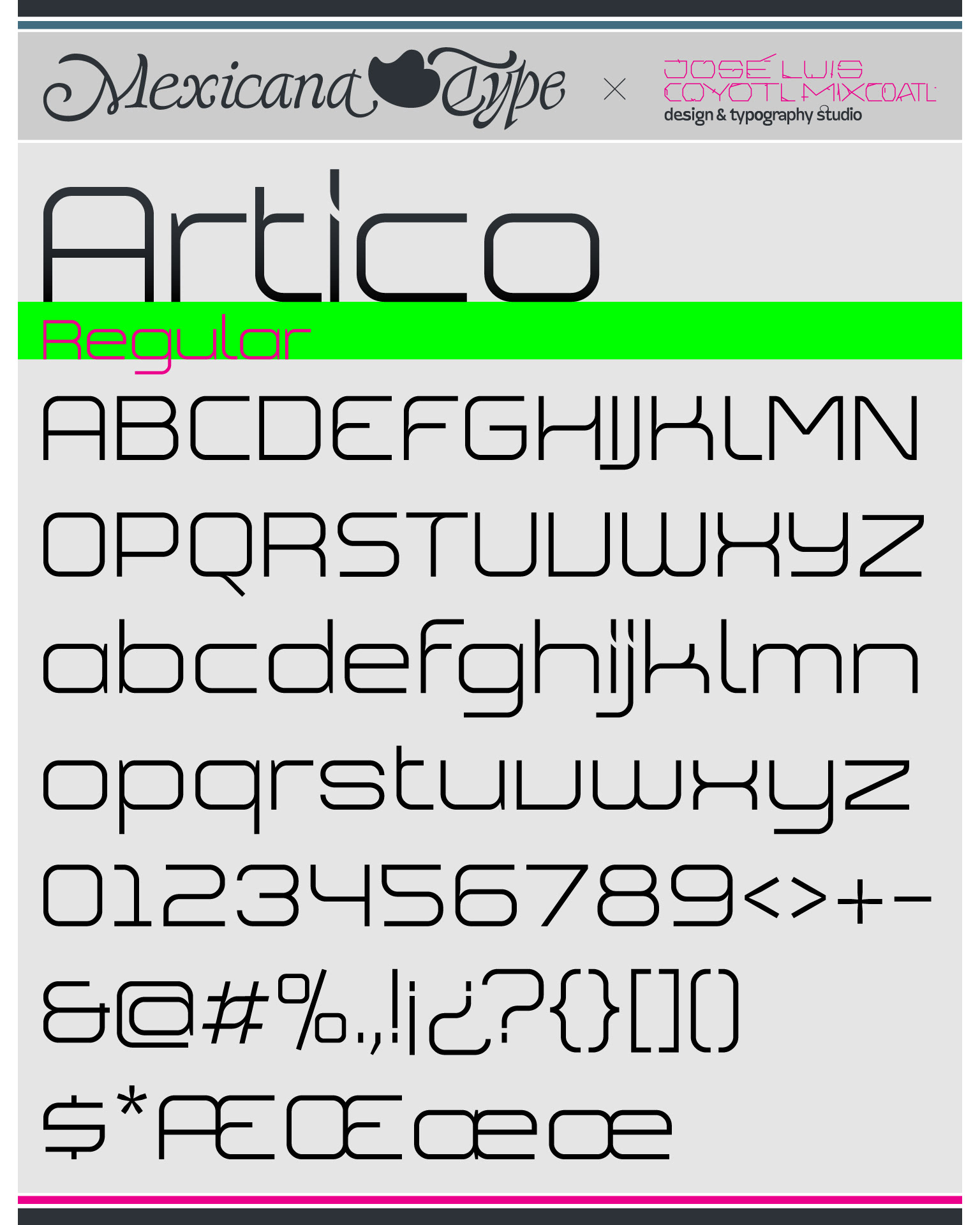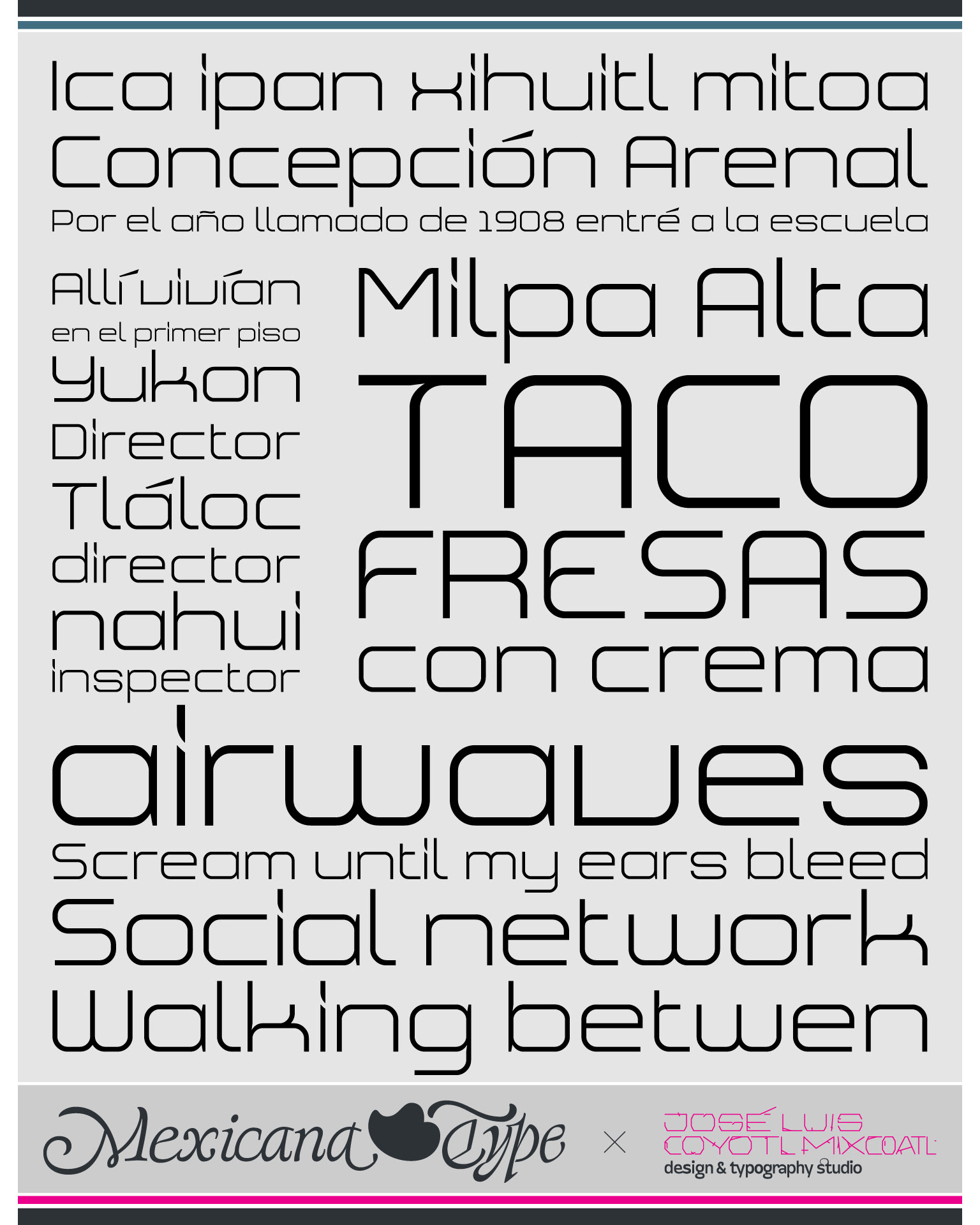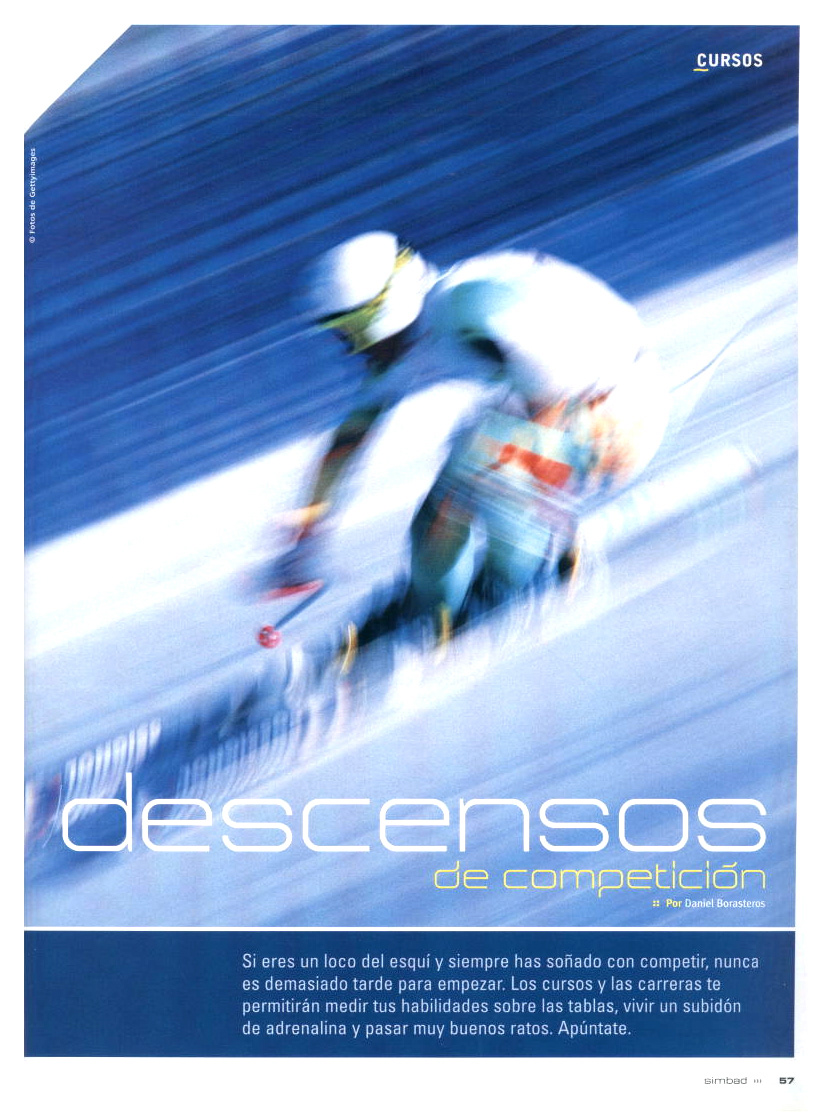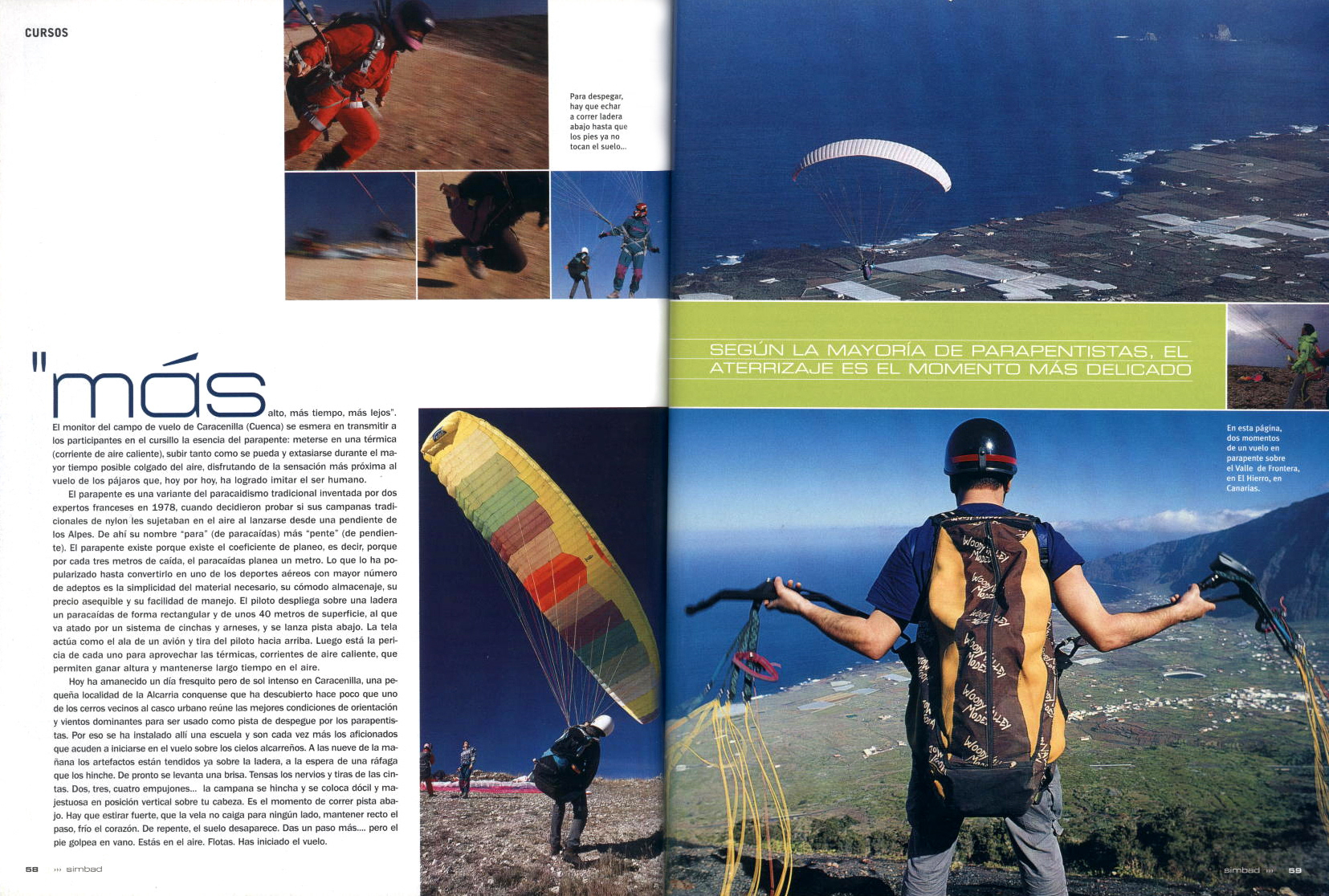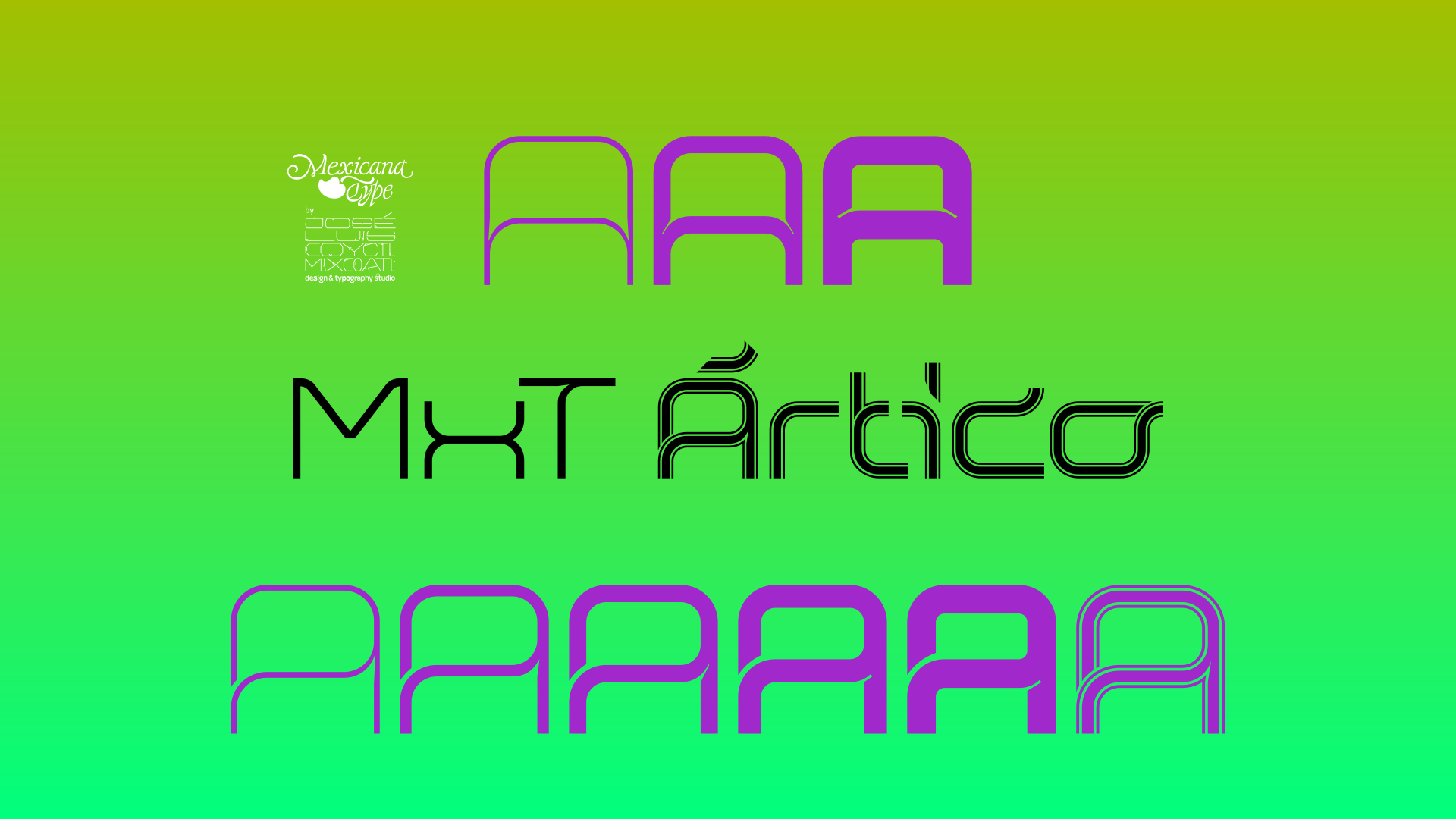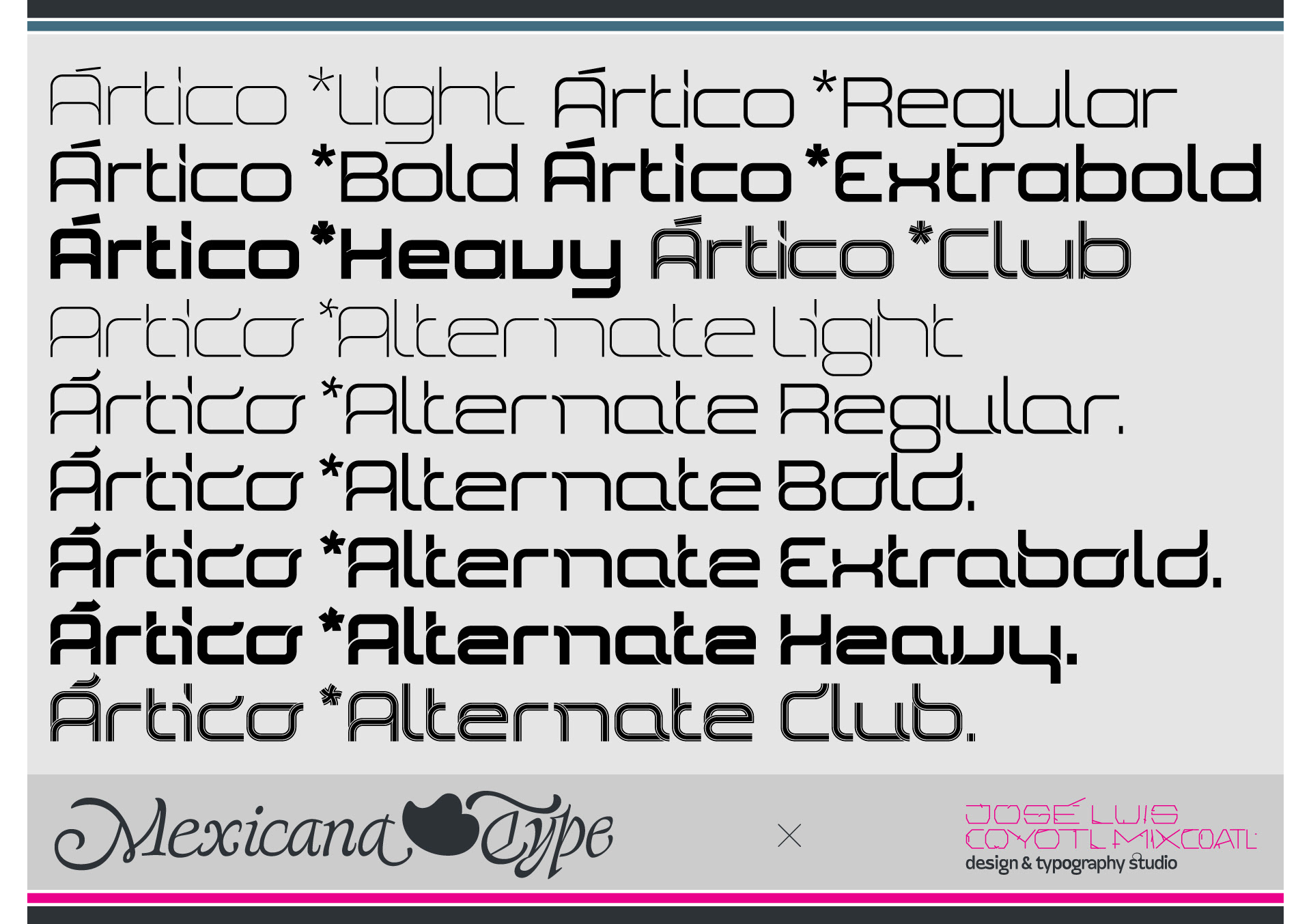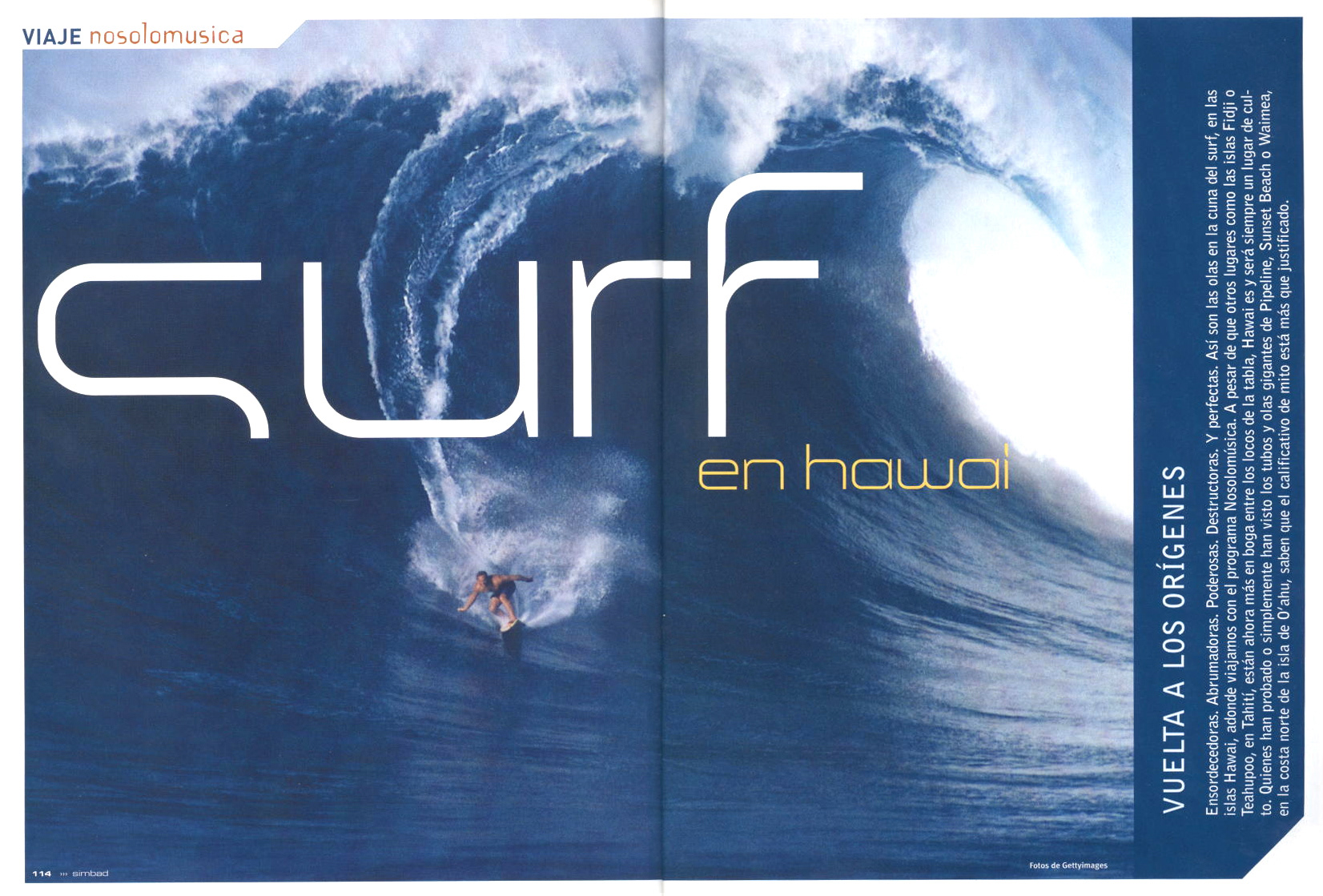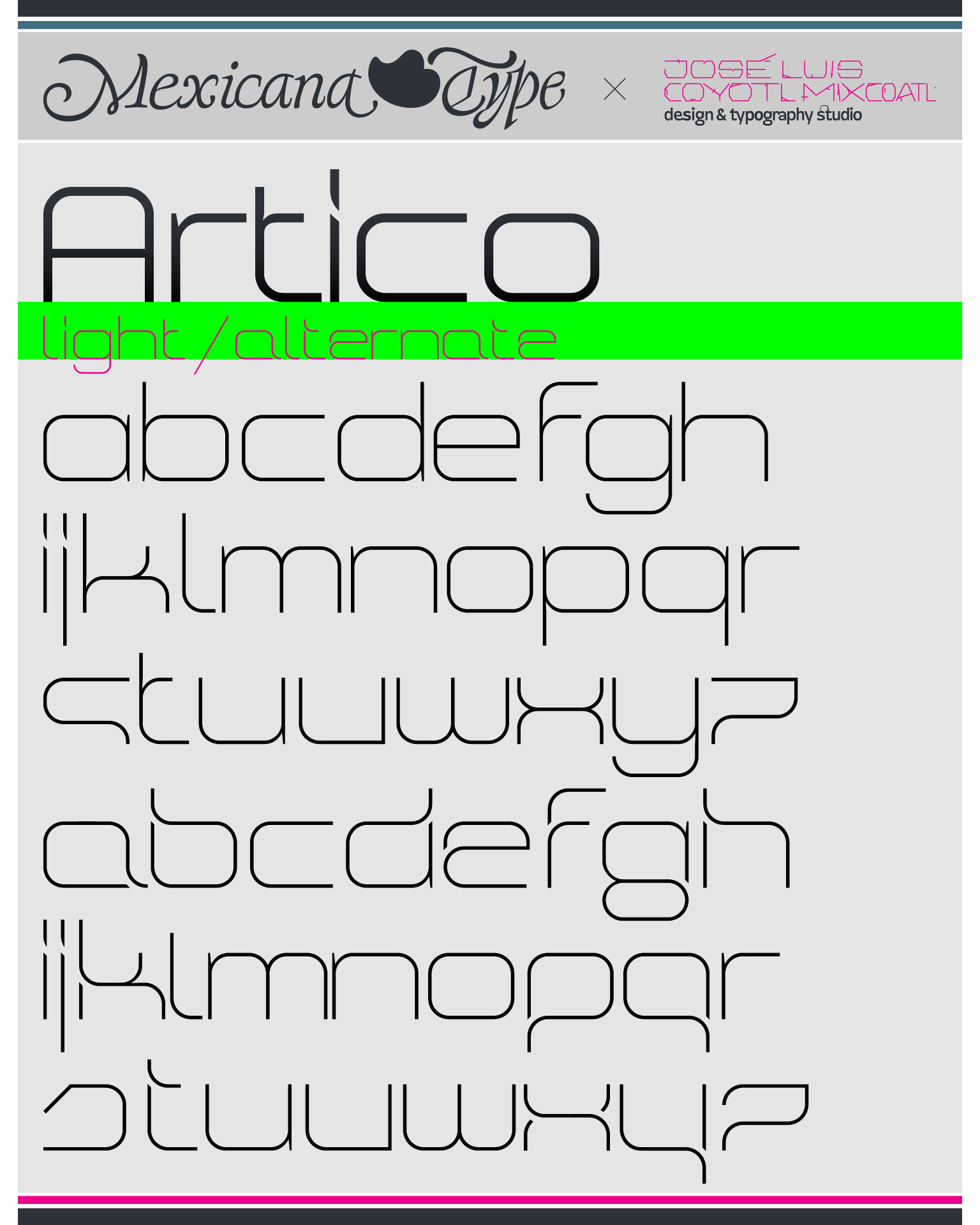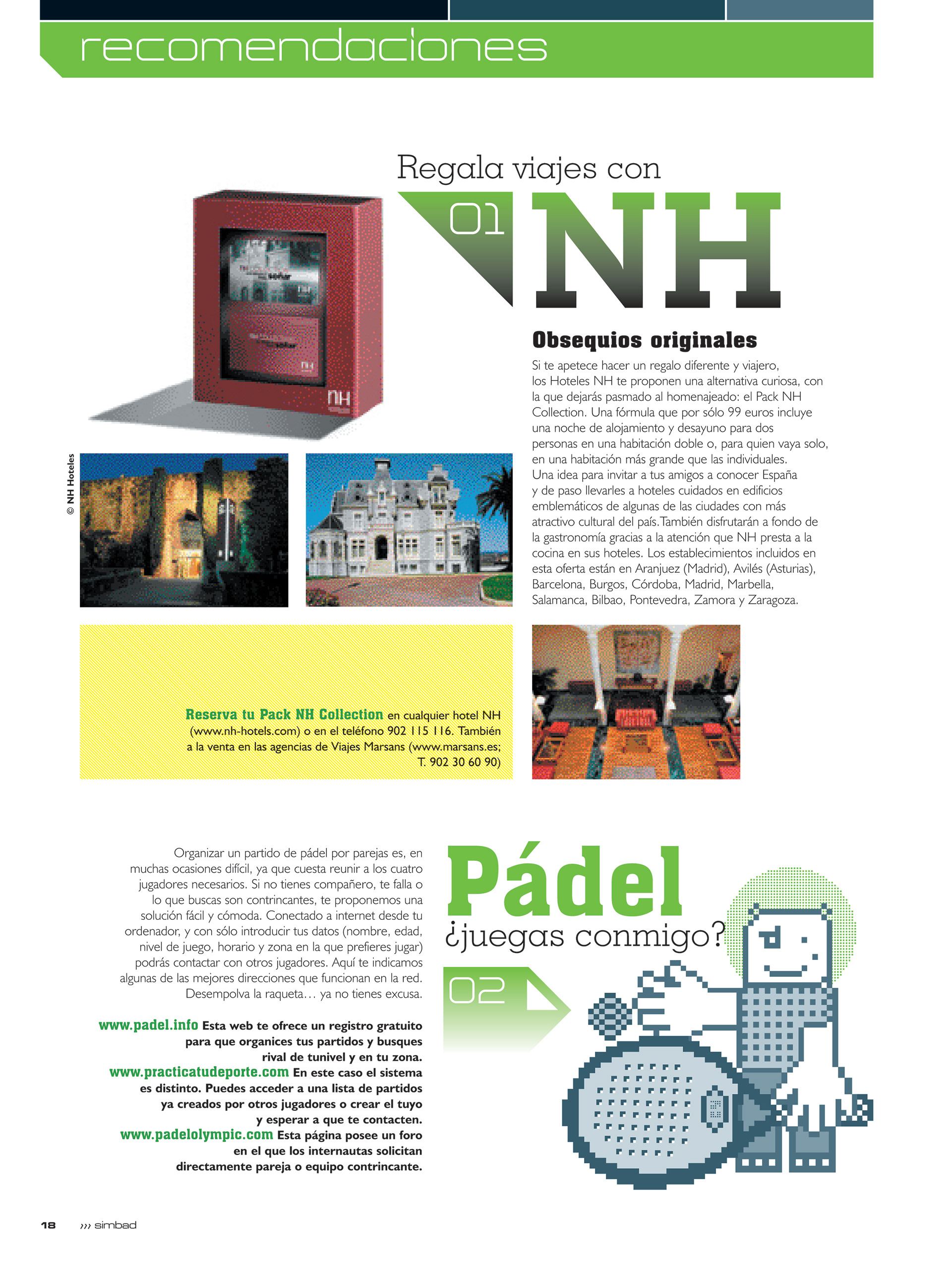
MxT Ártico fue un proyecto tipográfico desarrollado en 2004 para los títulos para la revista Simbad Travel & Sports, de la editorial española Versus, hecha bajo la dirección creativa de Domingo Martínez en el Estudio La Fe Ciega.
De trazo geométrico y modular, dada la naturaleza de la revista y su aplicación, de personalidad simple pero con acentos en algunos de sus caracteres y variantes, así como una versión adicional con los símbolos y elementos indicadores básicos usados en la revista. De cuerpo y estructura extendida, dado que fue desarrollada para títulos editoriales, generalmente para enfatizar una palabra o un conjunto de palabras limitado, permitía hacer algunos juegos de formas dado su uso display. Posteriormente se fueron desarrollando estilos adicionales para uso en proyectos personales, desarrollando dos estilos con 12 variantes en total, para hacerla más versátil.